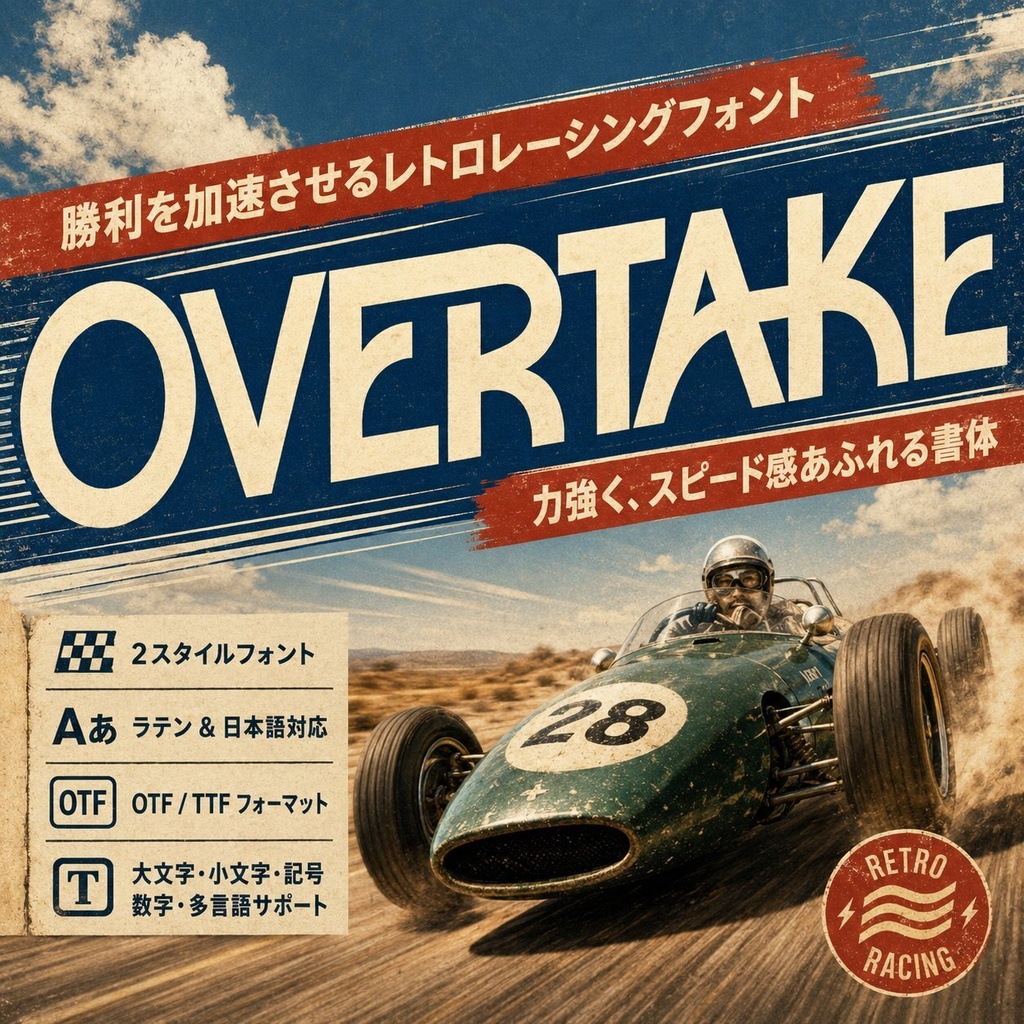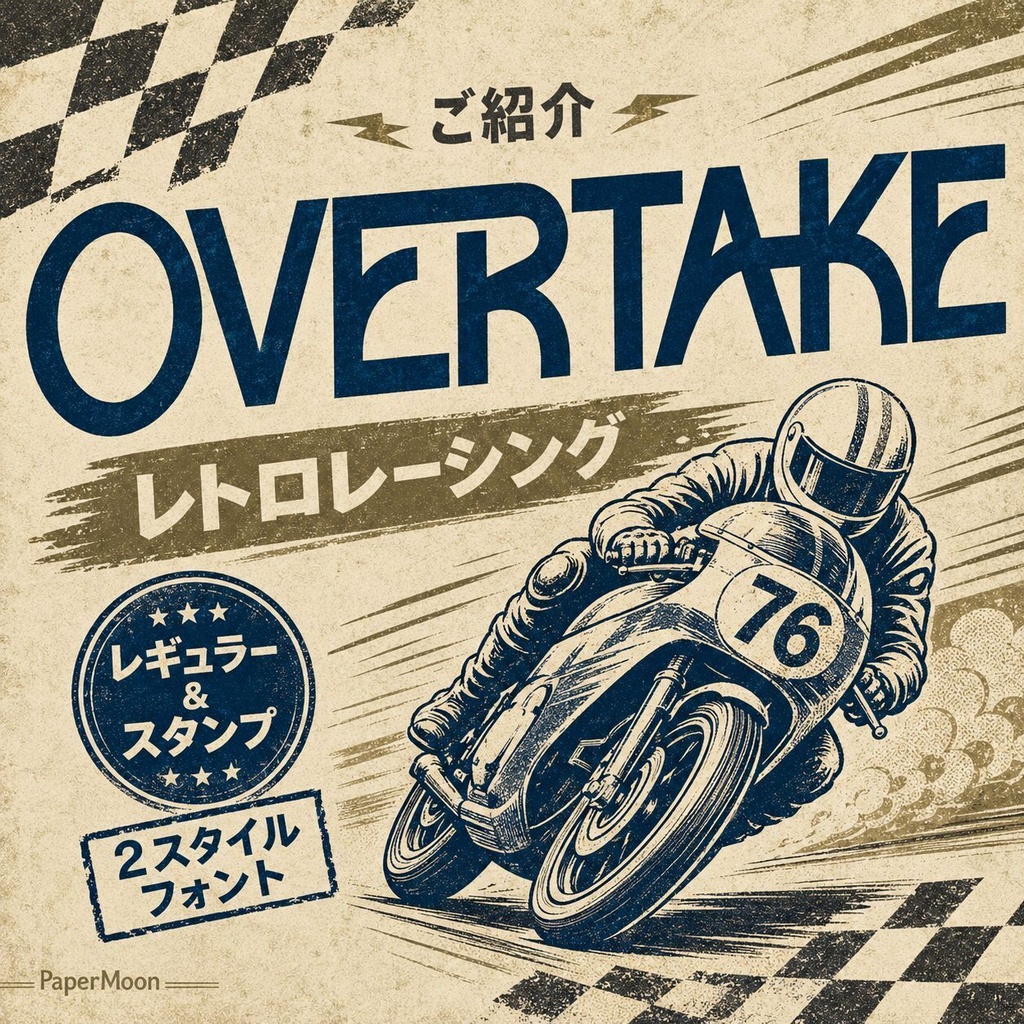
Overtake | レトロレーシング欧文ディスプレイフォント | ロゴ・グッズ向け Display Font
Overtake(オーバーテイク)は、レトロなレーシングモチーフから着想を得た、ノスタルジックで冒険心あふれる欧文(ラテン文字)ディスプレイフォントです。Regular と Stamp の2スタイルを収録し、ヴィンテージの風合いを持つ力強いボールドな字形で、見出しやロゴにひと目で強い印象を残します。太いストロークと高い視認性を両立し、オルタネート(代替字形)・リガチャ(合字)・多言語アクセントにも対応。モータースポーツやヴィンテージブランディング、アパレル、ストリート系のデザインまで幅広く使える一組です。 レーシングやスポーツをテーマにしたポスター、チームロゴ、Tシャツ・グッズの文字入れ、自動車・バイク関連のグラフィック、ヴィンテージ風のブランド制作、ストリートウェアやアーバンファッションのロゴなど、短い文字列で強いインパクトを残したい場面に最適です。 ### 収録内容 - Overtake Regular / Overtake Stamp の2スタイル - 各スタイル478グリフ - 大文字A–Z・数字・句読点・記号 - オルタネート(代替字形)・リガチャ(合字) - スタイリスティックセット・分数・序数・上付き文字などのOpenType機能(GSUB) - カーニング(GPOS)対応 - 多言語アクセント(ラテン拡張文字)対応 ### 対応文字 ラテン文字(欧文)の大文字アルファベット・数字・句読点に加え、アクセント付き欧州言語の文字(ラテン拡張文字)に対応しています。ひらがな・カタカナ・漢字、キリル文字、ギリシャ文字は未収録の欧文専用フォントです。 ### 用途 - レーシング・モータースポーツのポスター・フライヤー - チームロゴ・ブランドロゴ・ワードマーク - Tシャツ・アパレル・グッズの文字入れ - ヴィンテージブランディング・パッケージ - 自動車・バイク関連のグラフィック - ストリートウェア・アーバンファッションのデザイン - 見出し・イベント・映像タイトル ### 形式 - OTF(OpenType) - TTF(TrueType) - WOFF - WOFF2 ### 対応環境 Windows / macOS に対応します。Adobe Photoshop・Illustrator・InDesign など、フォントをインストールして使えるアプリケーション全般で利用できます。WOFF / WOFF2 はWebフォント(CSS @font-face)としても利用できます。 ### 利用許諾 商用制作には「商用利用」版、購入者自身の非商用作品・学習・練習・個人制作には「個人利用」版をお選びください。フォントファイルそのものの再配布・再販売を目的とした利用はできません。詳細な許諾条件は、購入前に各バリエーションの案内をご確認ください。